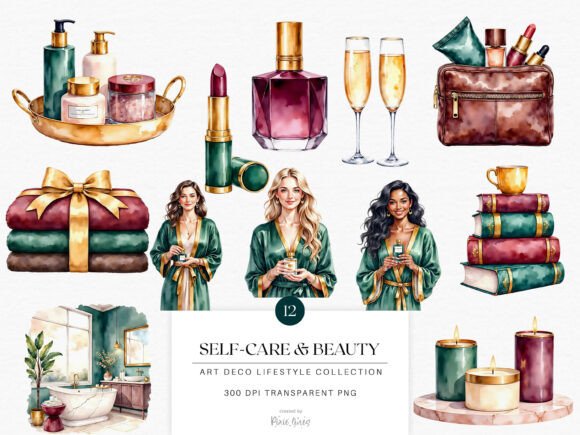
Art Deco Lifestyle, Self Care and Beauty
Jika anda sedang mencari aset berkualiti tinggi seperti Art Deco Lifestyle, Self Care and Beauty, pakej premium ini merupakan pilihan yang hebat untuk projek kreatif anda.
Dicipta dengan ketepatan, Art Deco Lifestyle, Self Care and Beauty menyediakan vektor yang bersih, tipografi yang licin dan lesen komersial untuk ketenangan fikiran.